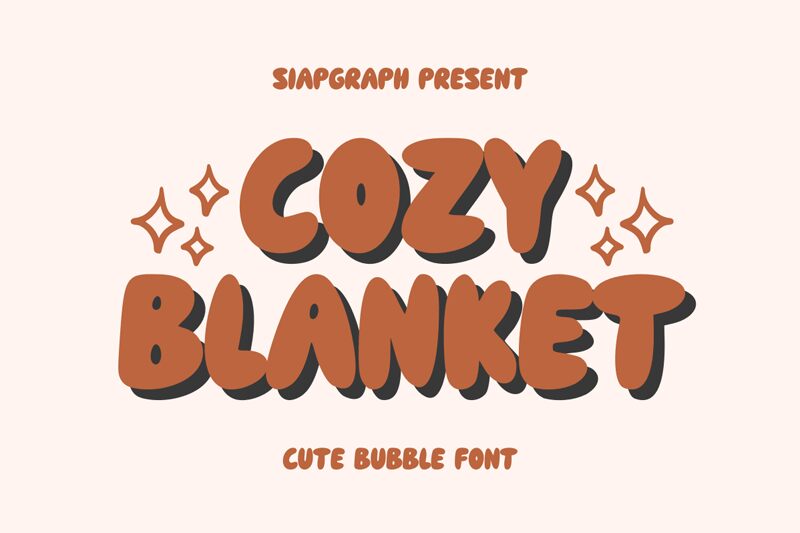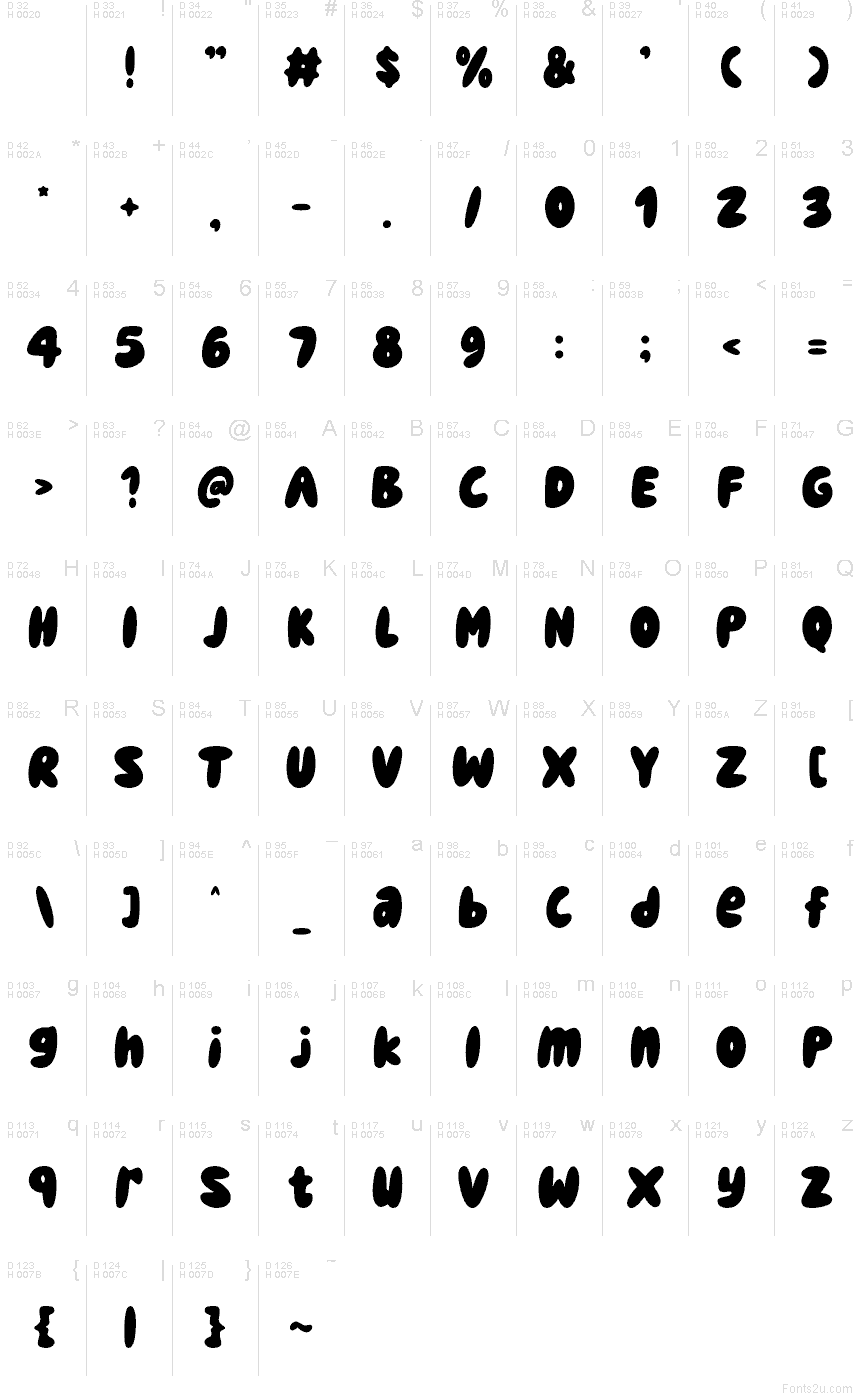
Cozy Blanket
Cozy Blanket - это бесплатный акцидентный шрифт с мягкими, «надутыми» очертаниями. Буквы выглядят не просто скругленными, а по-настоящему объемными, как будто они набиты мягким наполнителем. Плавные широкие изгибы и закрытые внутренние пространства придают дизайну расслабленный, уютный ритм, выделяя его на фоне стандартных шрифтов в стиле комиксов.
Такая «надутая» форма идеально подходит для детских книг, упаковки игрушек, приглашений на праздники, этикеток продуктов и веселых постов в соцсетях, где требуется теплый, жизнерадостный тон. Шрифт лучше всего смотрится в коротких заголовках и логотипах, где его дружелюбные и объемные формы создают яркий визуальный акцент без необходимости в лишнем декоре.